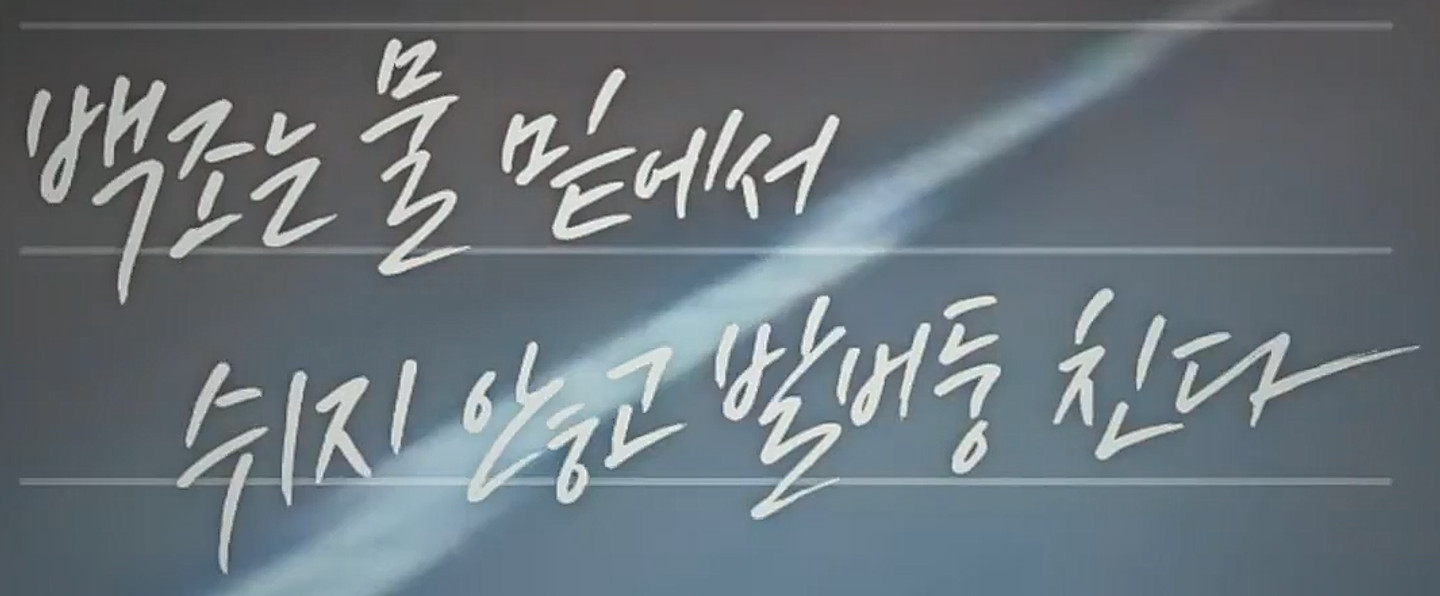
드라마 대행사에 나왔던 폰트 입니다. 솔폰트사의 데스페라도체, 펜시리즈체, 그리고 210 오늘은체와도 비슷하기는 하지만 조금 다릅니다. 알려주시면 정말 감사하겠습니다...^^
켈리그라피인 것 같습니다.
공병각 글씨체 같은데:-)
공병각 글씨체 같은데, 눈누에는 없네요,
캘리그라피 입니다. 폰트 아닙니다
캘리그라피 작가 '공작가'님의 캘리그라피 입니다. 폰트 아닙니다.